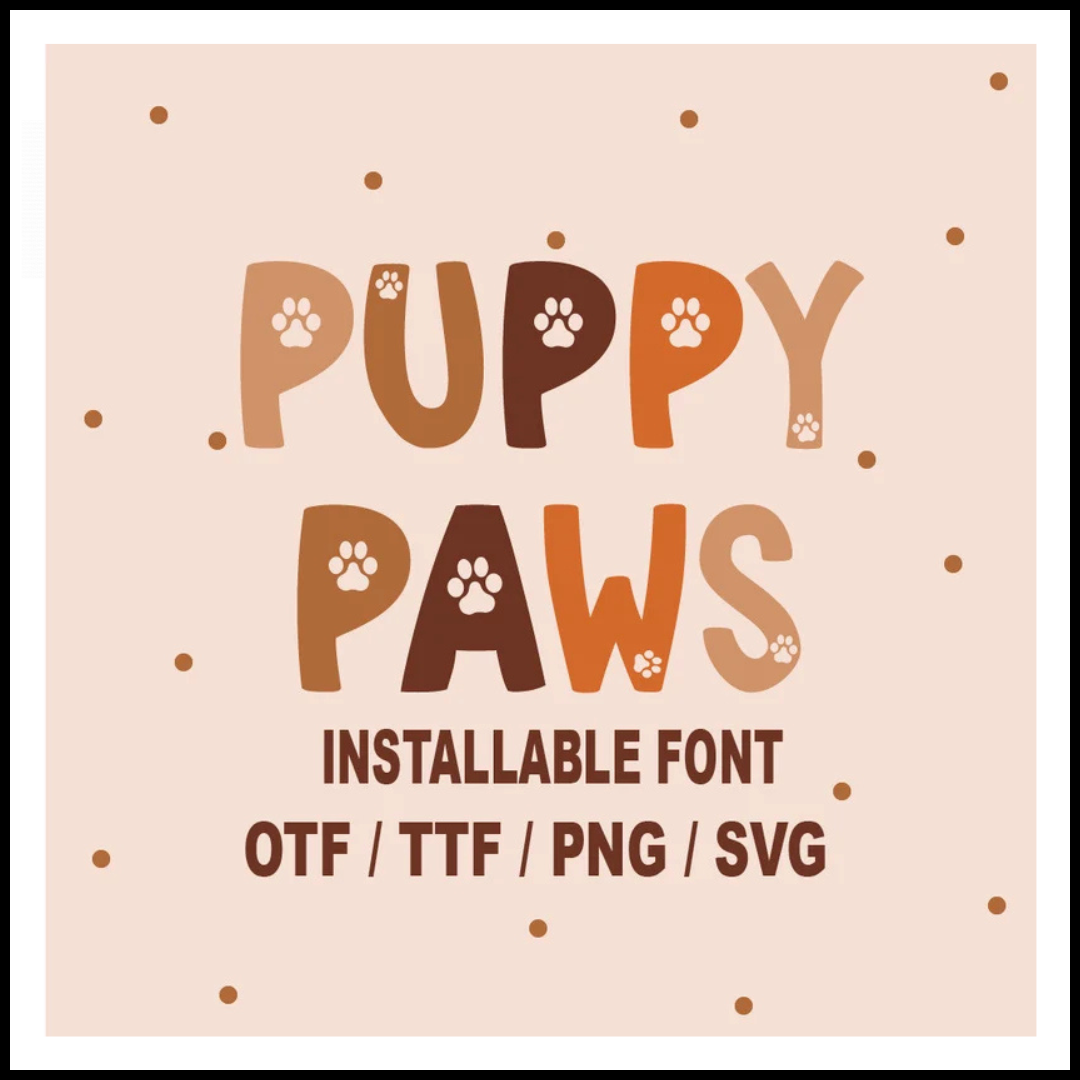
✨ Good Pawoo – Display Font
اجعل تصاميمك تنبض بالحيوية والشخصية مع Good Pawoo، الخط المثالي للمصممين الباحثين عن لمسة مرحة وعصرية!
يتميز هذا الخط بعناصر تصميم فريدة وأنيقة تُضفي طابعًا مميزًا على أي مشروع بصري. سواء كنت تصمم غلاف منتج، شعار علامة تجارية، ملصق إعلاني، أو منشور على وسائل التواصل، فإن Good Pawoo يمنحك لمسة احترافية لا تُقاوم.
???? مثالي لـ:
• تصميمات الأطفال
• مشاريع العلامات التجارية المبتكرة
• الشعارات الفريدة
• الإعلانات الجذابة
• أغلفة الكتب والمجلات
✨ مميزات الخط:
• تصميم Display مميز بستايل ممتع وجذاب
• جاهز للاستخدام في المشاريع الرقمية والمطبوعة